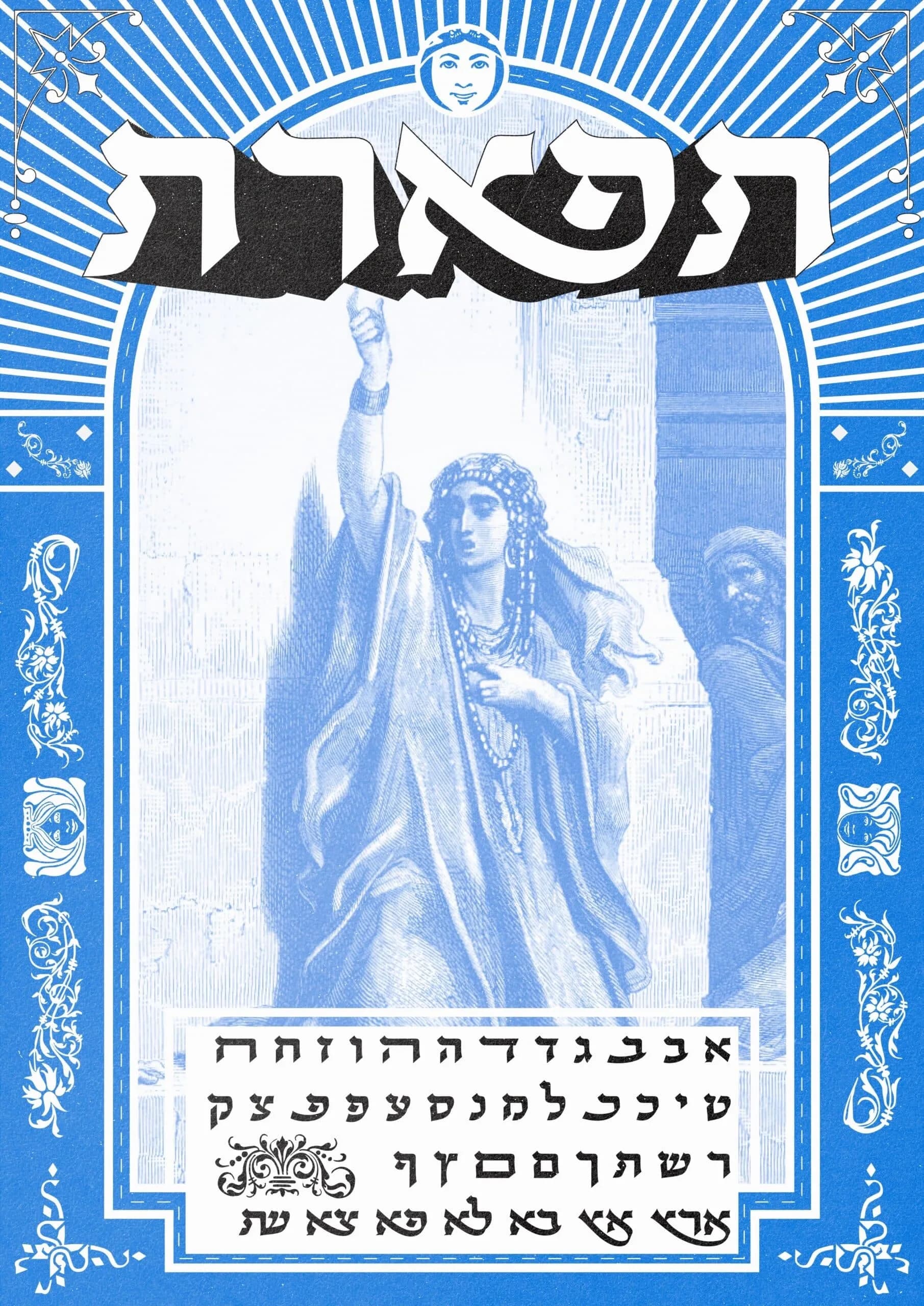
תִּפארֶת תִּפְאֶרֶת אותיות בעלות עיצוב אלגנטי וקולח. כל אות נושאת הילה קסומה, כאילו יש בה מסר סודי שמחכה להיפרם. הפונט מעניק אווירה של קסם פליאה ותפארת, מעולה עבור הזמנות, שילוט, כריכות ספרים, קלפים ויצירות אמנותיות אחרות בתחום זה.
Itay Ramati